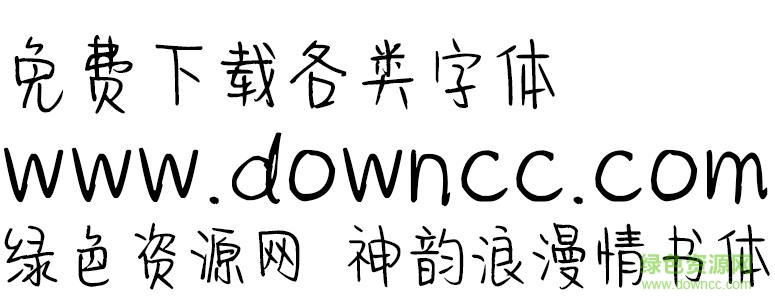
神韻浪漫情書(shū)字體是一款十分有趣的情書(shū)字體,通過(guò)在字體間加入了流暢的字體行文結(jié)構(gòu),讓你感受到十分舒適的視覺(jué)體驗(yàn),更能夠讓你在使用的時(shí)候獲得不錯(cuò)的字體視覺(jué)效果!
字體的樣式很精美,在使用的時(shí)候真是感受到了濃濃的情書(shū)氣息,很不錯(cuò),而且在眾多字體中我獨(dú)喜愛(ài)這一款字體!